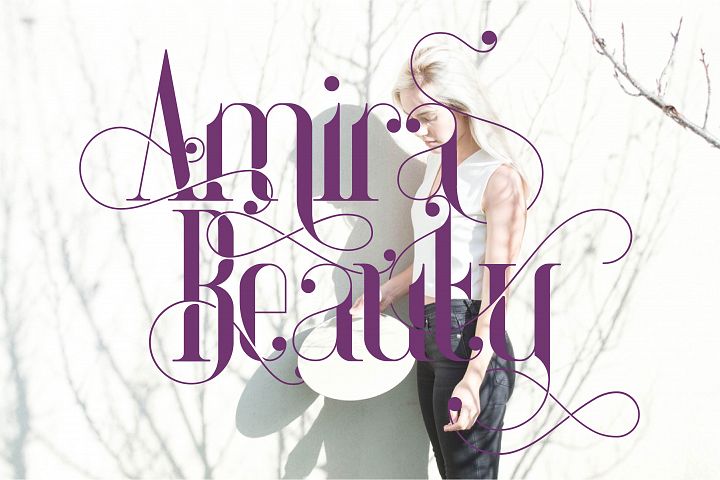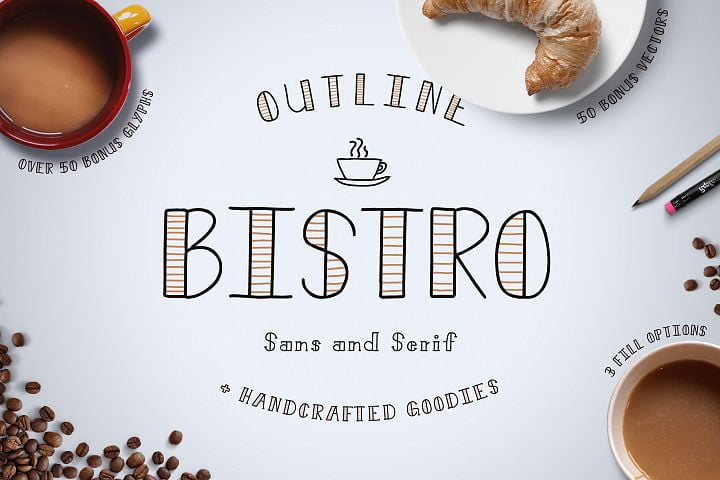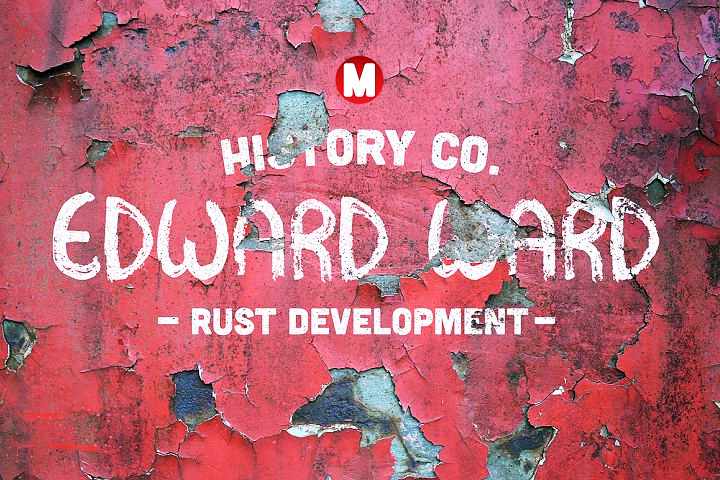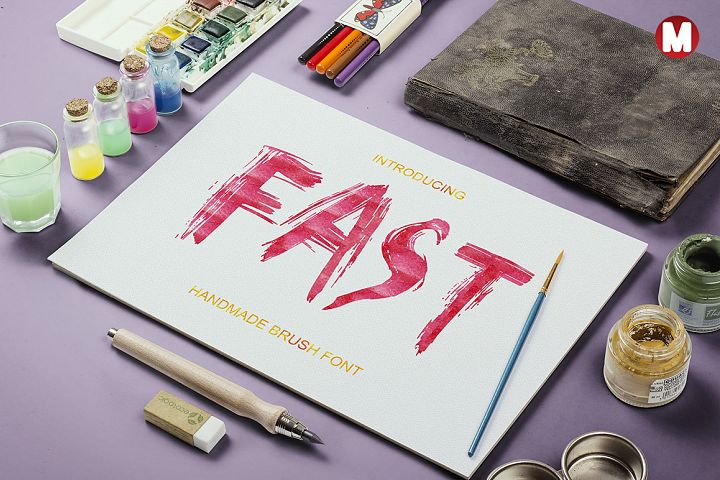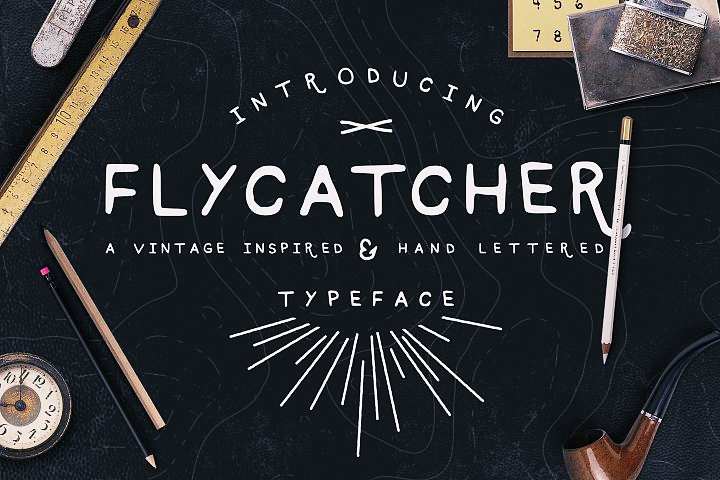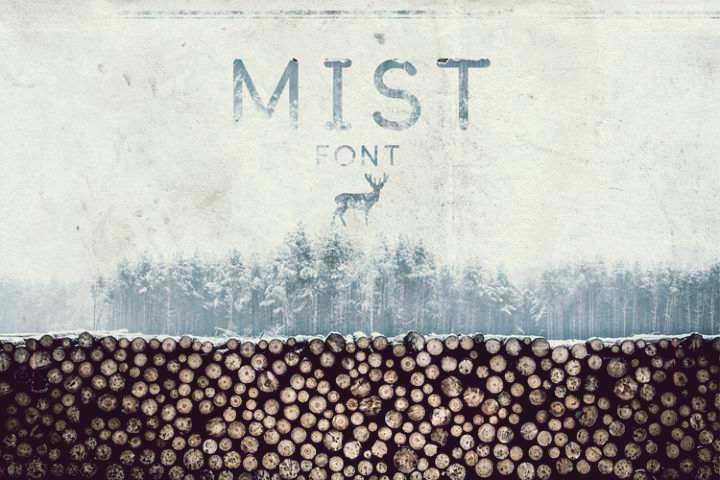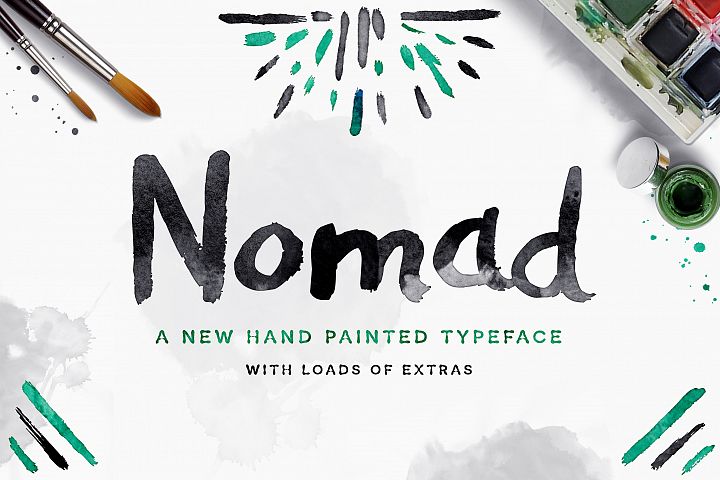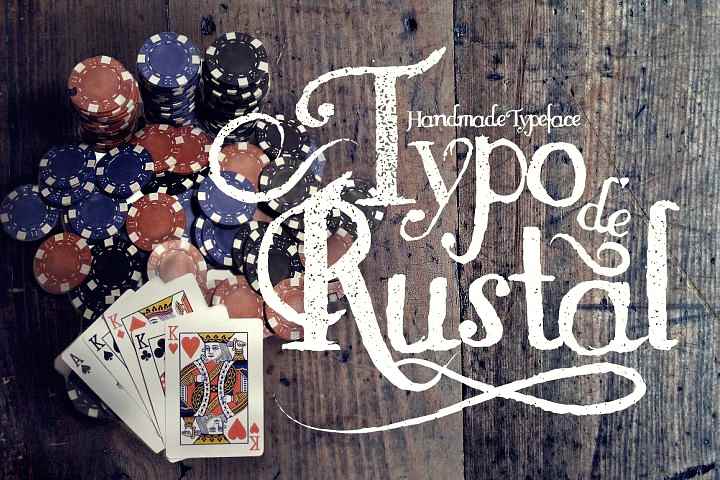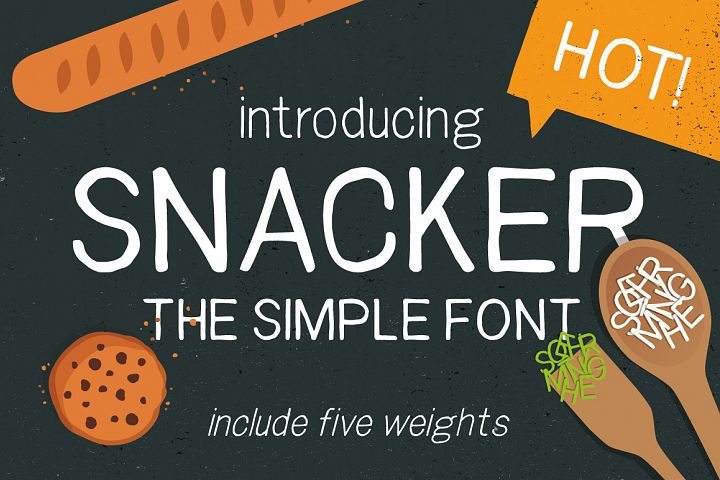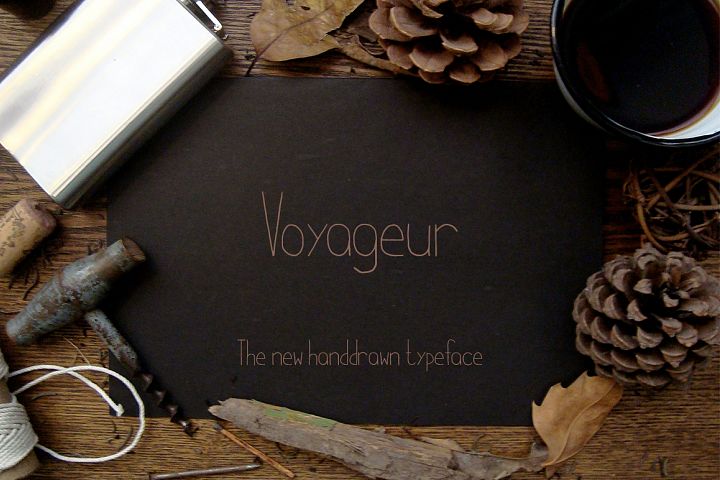
10 Font Terbaik Untuk Desain Kaos
10 Font Terbaik Untuk Desain Kaos – Referensi font terbaik buat kamu yang suka design kaos ataupun logo.
Menjual kaos sablon adalah cara murah untuk menghasilkan pendapatan tambahan. Dengan membuat kaos sablon sesuai permintaan seperti sablon kaos satuan. Selain itu, kalian juga bisa bikin desain kaos yang unik dan elegan dengan desain sendiri. Nah, Bagian yang sulit adalah membuat desain yang menarik yang banyak diminati oleh para pelanggan.
Memilih font yang tepat untuk baju Anda bisa membuatnya menarik dan diinginkan oleh pelanggan Anda. Coba gunakan salah satu dari 10 Font Terbaik Untuk Desain Kaos berikut ini.
1. Snacker
Snacker adalah jenis huruf sans-serif sederhana yang terlihat sangat menarik untuk desain kaos. Tepi bulat font sedikit melembutkan teks, sedangkan spasi yang lebar membuat kata-kata mudah dibaca. Tersedia lima variasi untuk font Snacker, sehingga Anda dapat bereksperimen dengan teks T-shirt hingga cocok dengan keseluruhan desain Anda.
2. Flycatcher
Bahkan lebih bulat daripada Snacker, Flycatcher adalah font yang unik dan khas yang sempurna untuk desain T-shirt retro. Pas dengan font font untuk memberikan gaya vintage untuk T-shirt Anda.
3. Nomad
Keluarkan sisi petualangan Anda dengan Nomad, font yang sedikit kasar yang masih sangat jelas. Dengan gayanya yang menyenangkan, gaya yang dilukis dengan tangan, Nomad adalah font yang fantastis untuk menarik bagi individu yang suka berpetualang, yang dapat membantu desain kaos Anda menjadi viral.
4. Edward
Ingin memberikan kaos kustom Anda dengan tampilan seperti buatan tangan? Edward memiliki tulisan tangan asli yang kasar, dan mudah dibaca. Gunakan itu untuk membuat kaos Anda dengan nama merek Anda atau tambahkan slogan favorit Anda.
5. Fast
Playful, fun and friendly, Fast sangat cocok untuk desain kaos yang unik. Padukan dengan grafis tebal dan warna-warna cerah untuk membuat kemeja yang elegan. Meskipun unik dan menarik, Fast masih mudah dibaca, yang sangat penting untuk font apa pun yang muncul pada kaos.
6. Mist
Menyerupai kata-kata misterius yang memudar ke dalam kabut, Mist adalah jenis huruf biasa namun khas. Tersedia dalam huruf besar dan kecil dengan lebih dari 40 glyphs, Mist sangat ideal untuk teks T-shirt apa pun. Padukan dengan fotografi menakjubkan untuk membuat kesan abadi.
7. Voyageur
Voyageur bukan termasuk font serif, tetapi memiliki banyak gaya. Percobaan dengan jenis huruf yang ditarik dengan tangan, untuk menemukan desain yang sempurna untuk baju Anda.
8. Rustal Typo
Mencari jenis huruf yang memiliki tepi vintage, namun masih cukup kasual untuk digunakan pada T-shirt dengan daya tarik yang luas? Rustal Typo adalah font pedesaan yang cocok untuk kaos khusus yang unik. Gunakan huruf-huruf yang sedikit pudar ini untuk membuat desain kaos Anda diminati banyak pelanggan.
9. Amira Beauty
Amira Beauty adalah font bunga khas dengan ekor melengkung besar pada banyak huruf. Terinspirasi oleh keindahan bunga Amira, ini adalah font yang sangat elegan, tidak hanya untuk T-shirt tetapi untuk semua produk digital Anda.
10. Bistro
Cicipi kopi pagi Anda sambil mengenakan T-shirt yang ditulis di Bistro, font garis besar di mana setiap huruf disempurnakan dengan interior dua warna. Font ini tersedia dalam gaya serif dan sans-serif, sehingga Anda dapat bereksperimen dengan berbagai desain T-shirt untuk menemukan salah satu yang memberikan hit seperti kafein yang Anda cari.